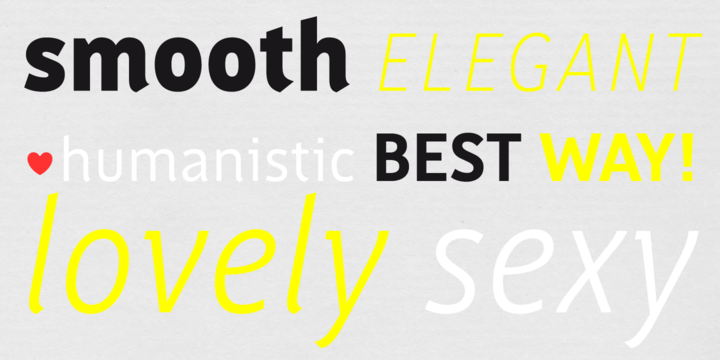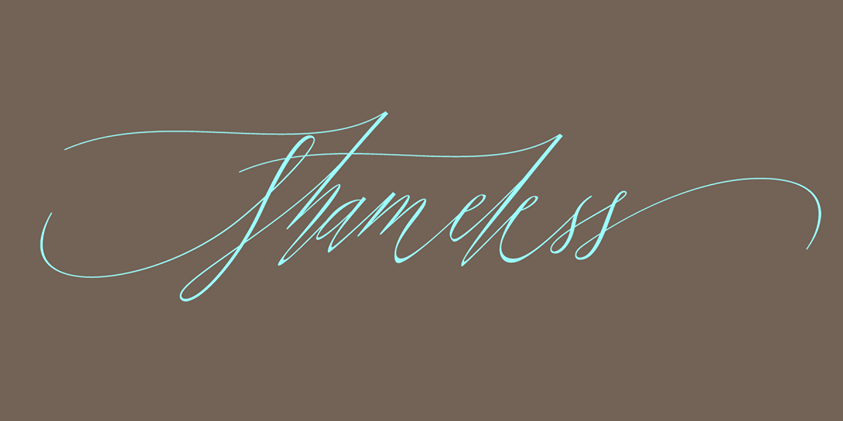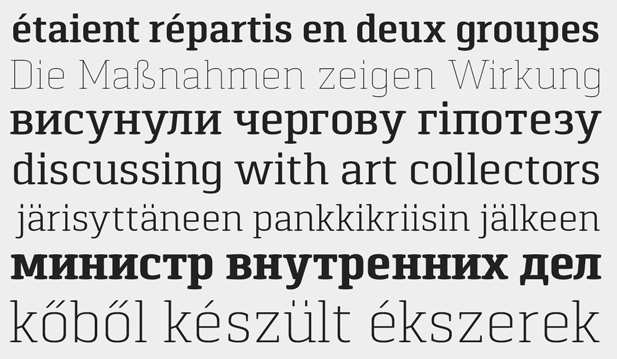
Fresh Fonts 14 | 03 Pancetta Serif, Shameless & Saya FY
Zahlreiche Neuveröffentlichungen kommen in der der 2. Januarwoche von Latinotype aus Chile, Mint Type aus Kiev, von Positype, Georgia, und Laura Worthington, US-Westküste, der französichen Crowd-Foundry FONTYOU und der Indian Type Foundry.
Mit Pancetta Serif baut Andriy Konstantynov seine Eurostile-Alternative Pancetta zu einer Großfamilie aus. Mit acht Schriftschnitten, passenden Kursiven, einer Web- und einer Pro-Version, die im lateinischen, osteurpäischen und kyrillischen Sprachraum gleichermaßen zu Hause ist, steht eine Familie für die grenzenlose Kommunikation ins nicht-lateinische Ausland zur Verfügung.
Federnd leicht und verführerisch und eher verrucht – nie naiv. Shameless basiert auf Neil Summerours Handschrift mit einem Kuretake Zig CocoIro Stift, den er liebt. Für den ausschweifenden Gebrauch von Kontext-Alternates, die ein fließendes auf und ab der Buchstabenverbindungen ermöglichen, schöpft der Shameless-Zeichenvorrat aus dem Vollen: allein die „Standard“-Version enthält 2200 Glyphen. Die „Deluxe“-Version bringt es sogar auf 2398 Glyphen. Shameless bringt Charakter in Headlines, Displays und Verpackungen. Verführerisch hingehaucht, leicht doch mit „Kante“.
Kurz erwähnt: Positypes Lust bekommt einen schwungvollen Partner – Lust Script.
Die Crowd-Schriftenschmiede Fontyou mit physischem Sitz in Paris, bereichern das FontShop-Angebot diese Woche mit gleich fünf neuen Entwürfen: Brixton FY, Vanille FY, Vidok FY und Saya FY. Saya FY ist eine modern-vielseitig und elegante Sans-Familie, gemeisam entwickelt von Jeremie Hornus, Adrien Midzic und Alisa Nowak. Sowohl für Texte als auch für den Display-Einsatz eignet sich die robuste Brotschrift mit sechs Strichstärken von Thin bis Black und passenden Kursiven.
Schmal-laufende Lettern und eine ausgewogene Verbindung, gerundeten Formen mit kantigen Abstrichen, verleihen der Schrift einen konsistenten Auftritt. Saya FY liegt im Print- und Webformat vor – ein idealer Kandidat für cross-mediale Projekte. Wie jede Woche erscheinen Kurzschriftmuster auf unserem Pinterest-Board »Fresh Fonts«.